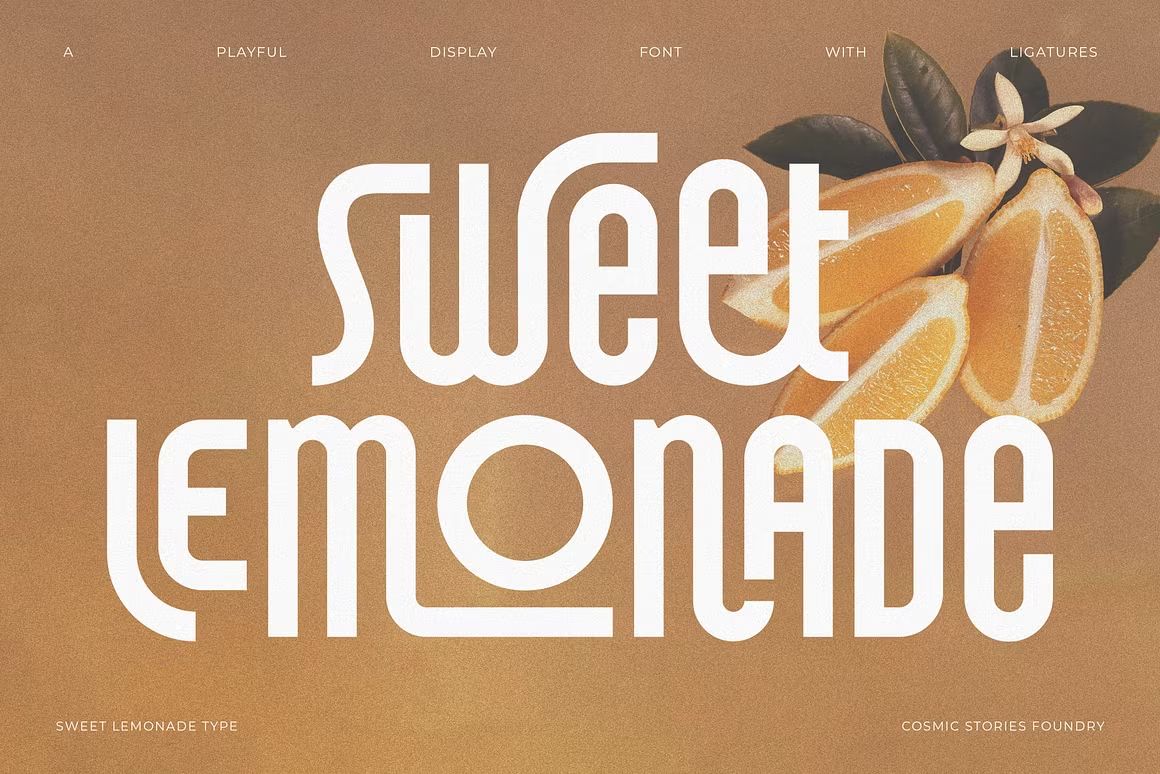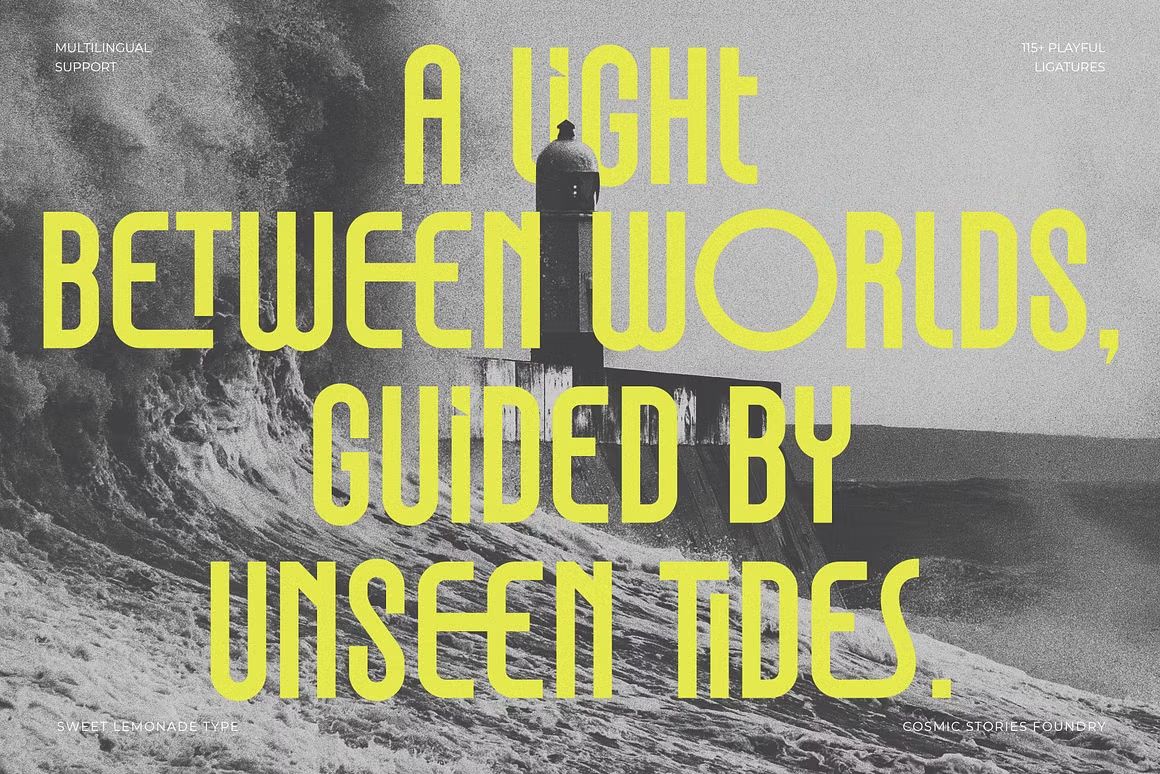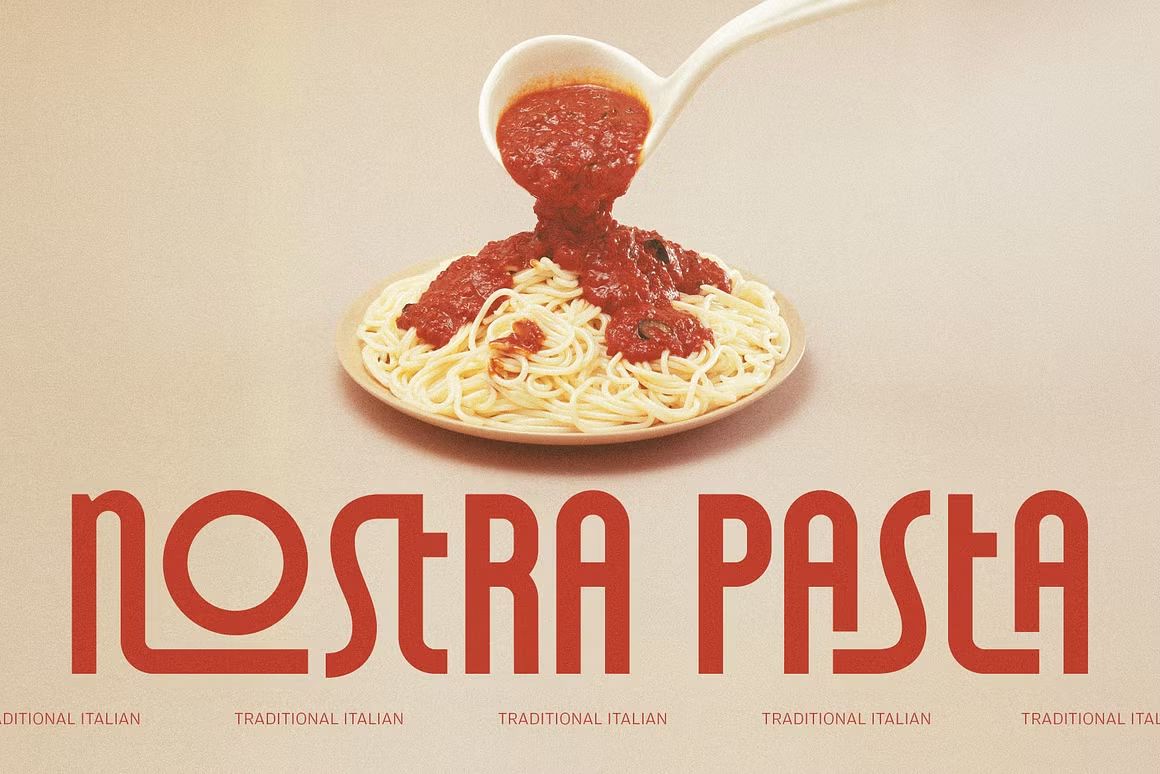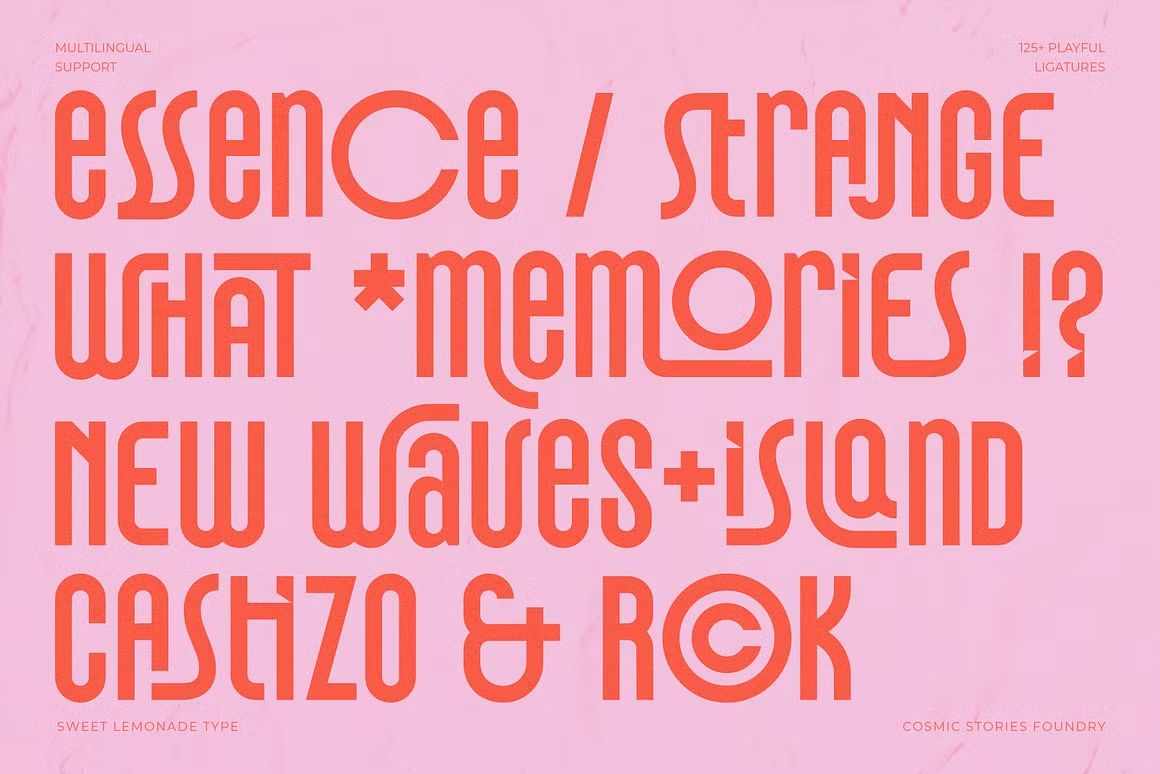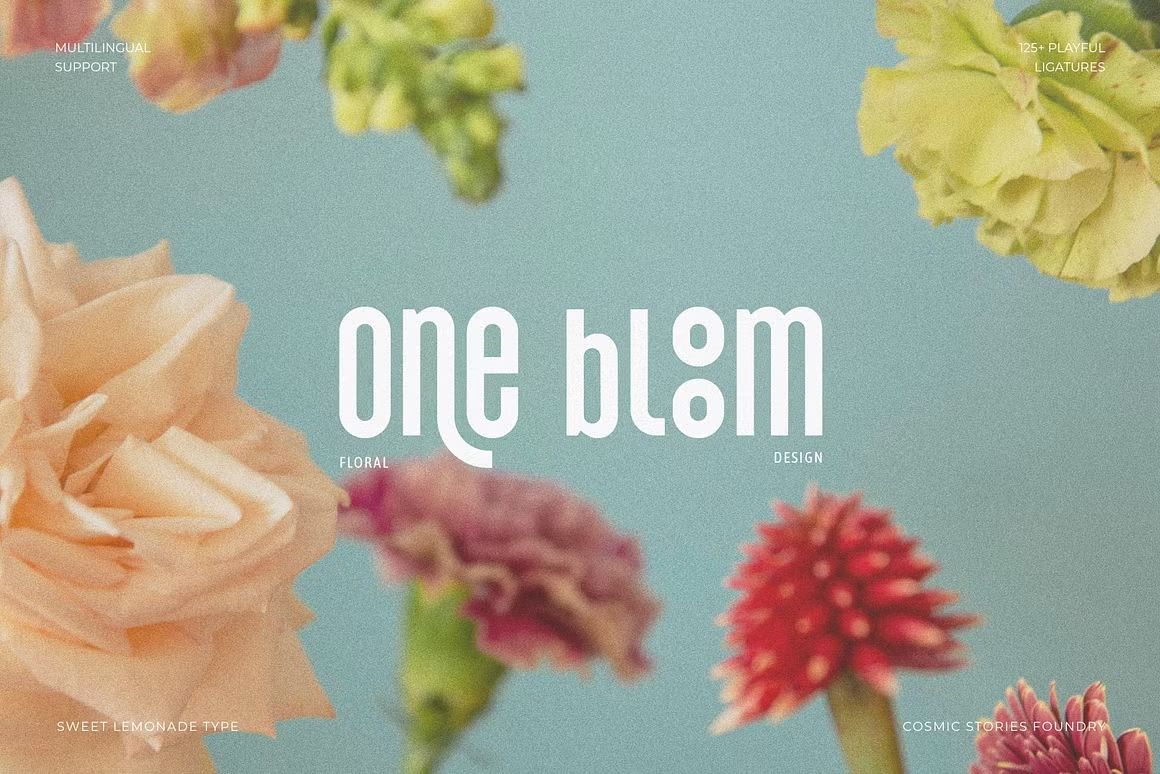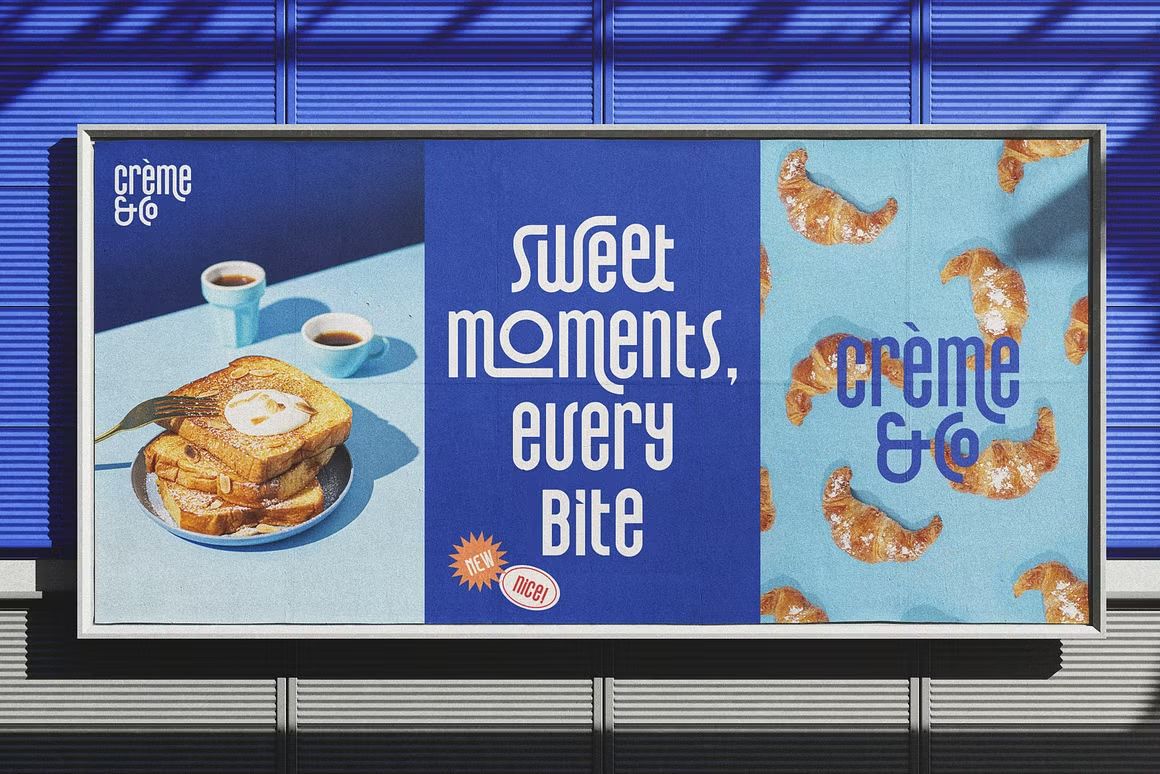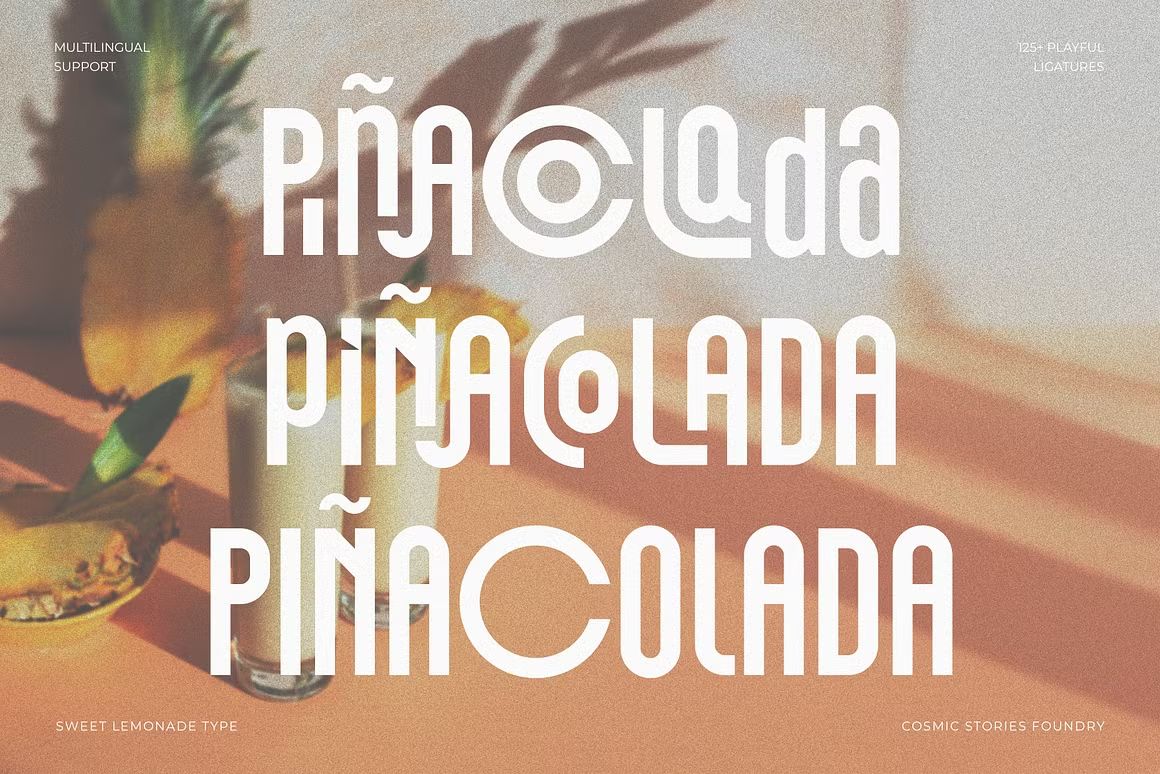
Sweet Lemonade – Sans Serif Font
Sweet Lemonade adalah font sans serif dengan gaya modern dan playful, cocok untuk desain branding, poster, kemasan produk, dan proyek kreatif yang membutuhkan tampilan ceria dan segar.
Sweet Lemonade adalah font sans serif dengan tampilan modern, segar, dan playful. Desainnya yang bersih namun penuh karakter menjadikannya pilihan ideal untuk berbagai proyek kreatif seperti branding, kemasan produk, poster, dan media sosial. Font ini menghadirkan kesan ceria, ramah, dan profesional dalam satu tampilan yang mudah dipadupadankan.
Fitur unggulan:
• Gaya sans serif modern dengan sentuhan playful dan segar
• Cocok untuk branding, kemasan produk, poster, dan media sosial
• Termasuk huruf besar, huruf kecil, angka, dan simbol
• Ideal untuk proyek cetak maupun digital dengan tampilan ceria dan bersih